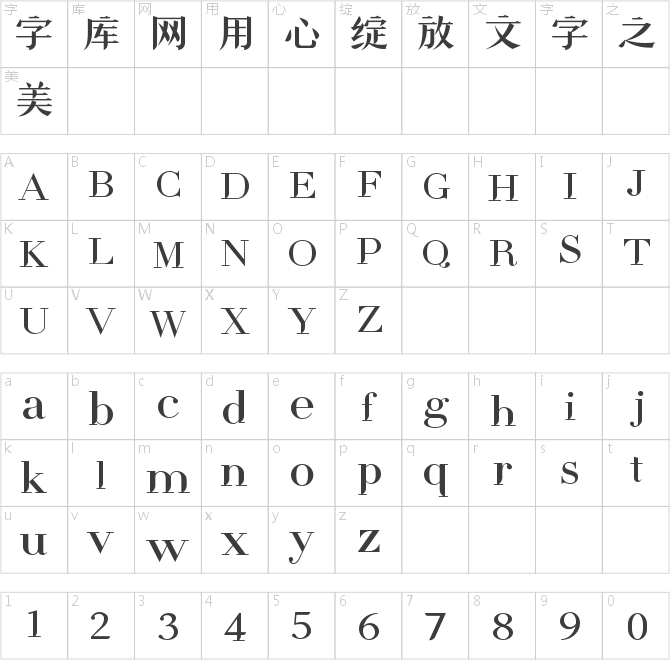
潮字社國風冉宋簡 詳情頁
字體名稱: 潮字社國風冉宋
作者版權(quán): 銳字潮牌
潮字社國風冉宋簡
潮字社國風冉宋簡字體字庫是一款讓人賞心悅目、百看不厭的中文字體,適合各類廣告和產(chǎn)品包裝設(shè)計應(yīng)用,字體大小1.64MB,格式為ttf字體,上傳用戶是Apple,作者/版權(quán)方為銳字潮牌